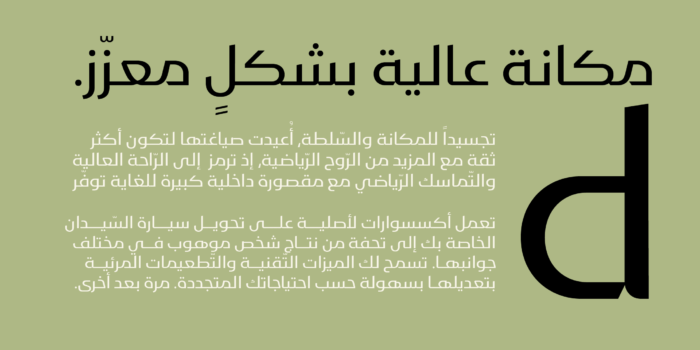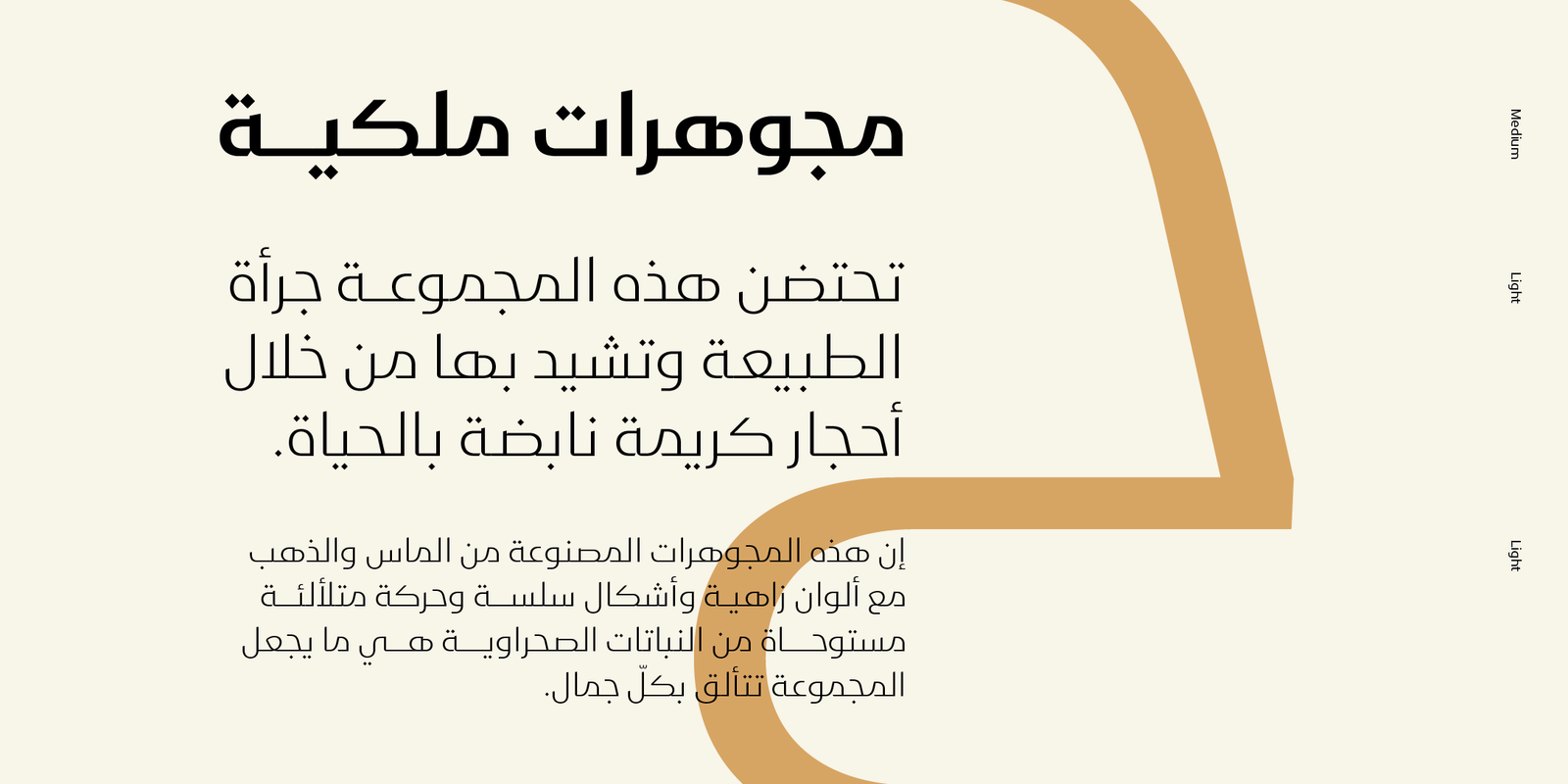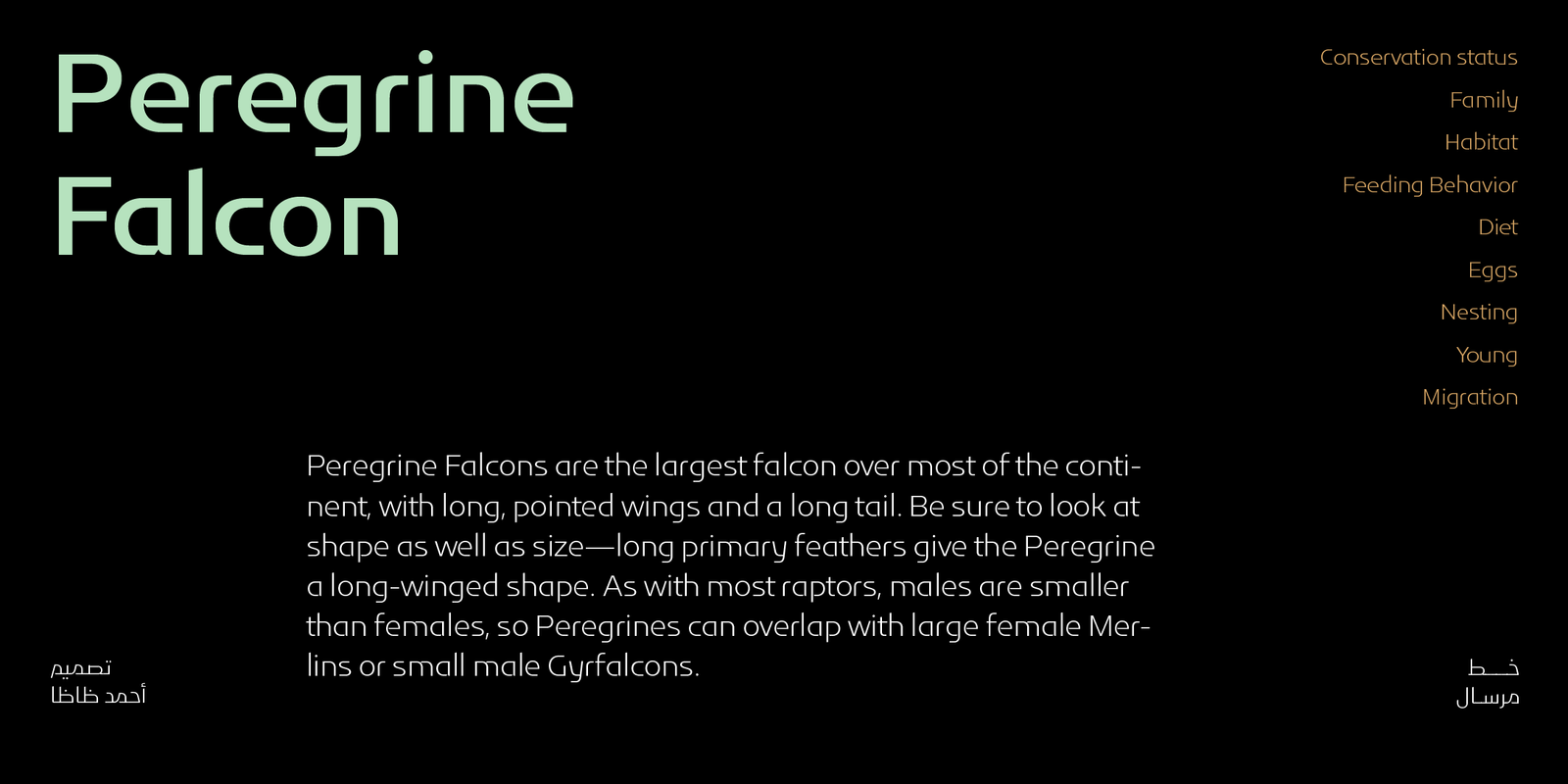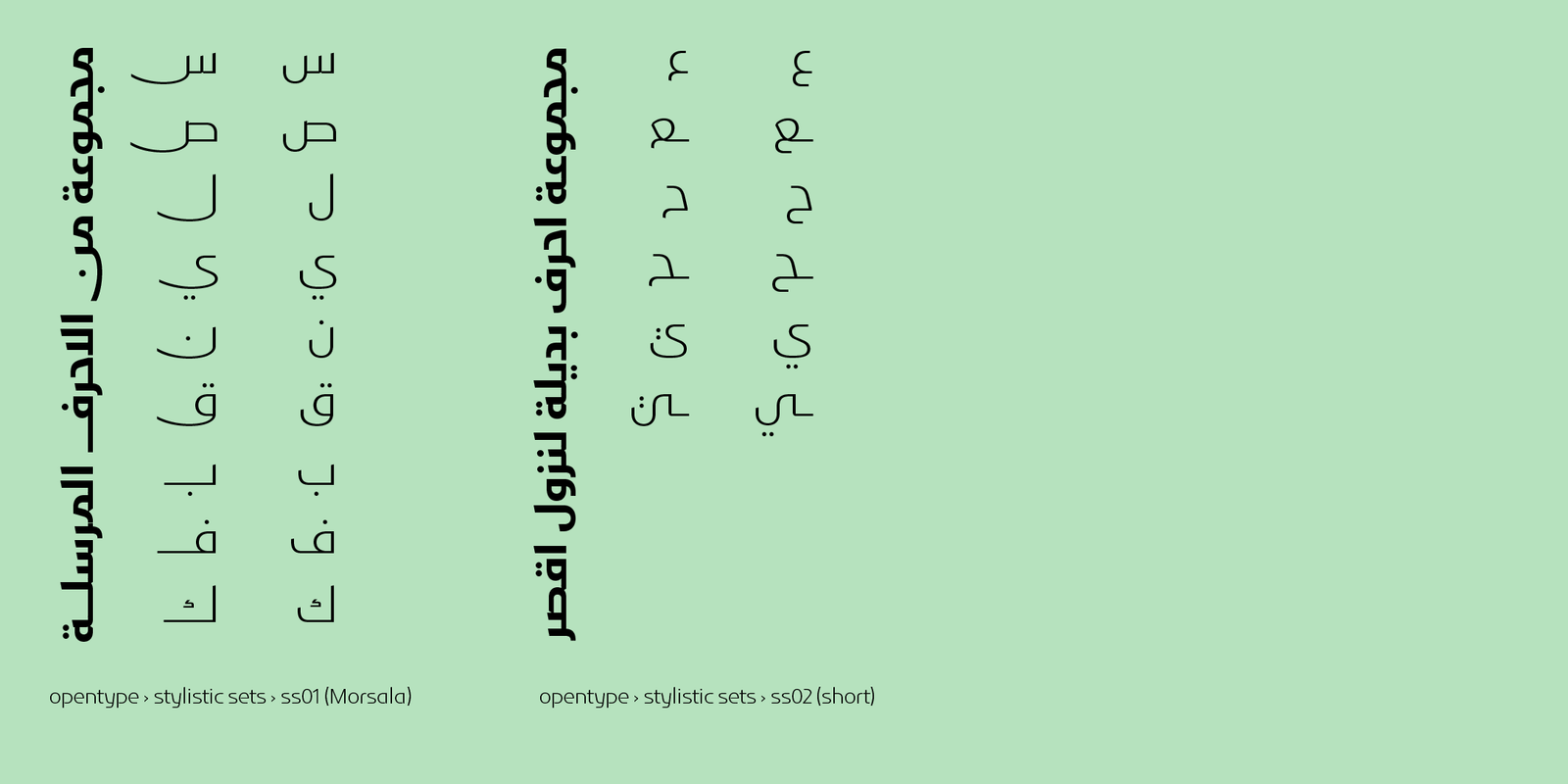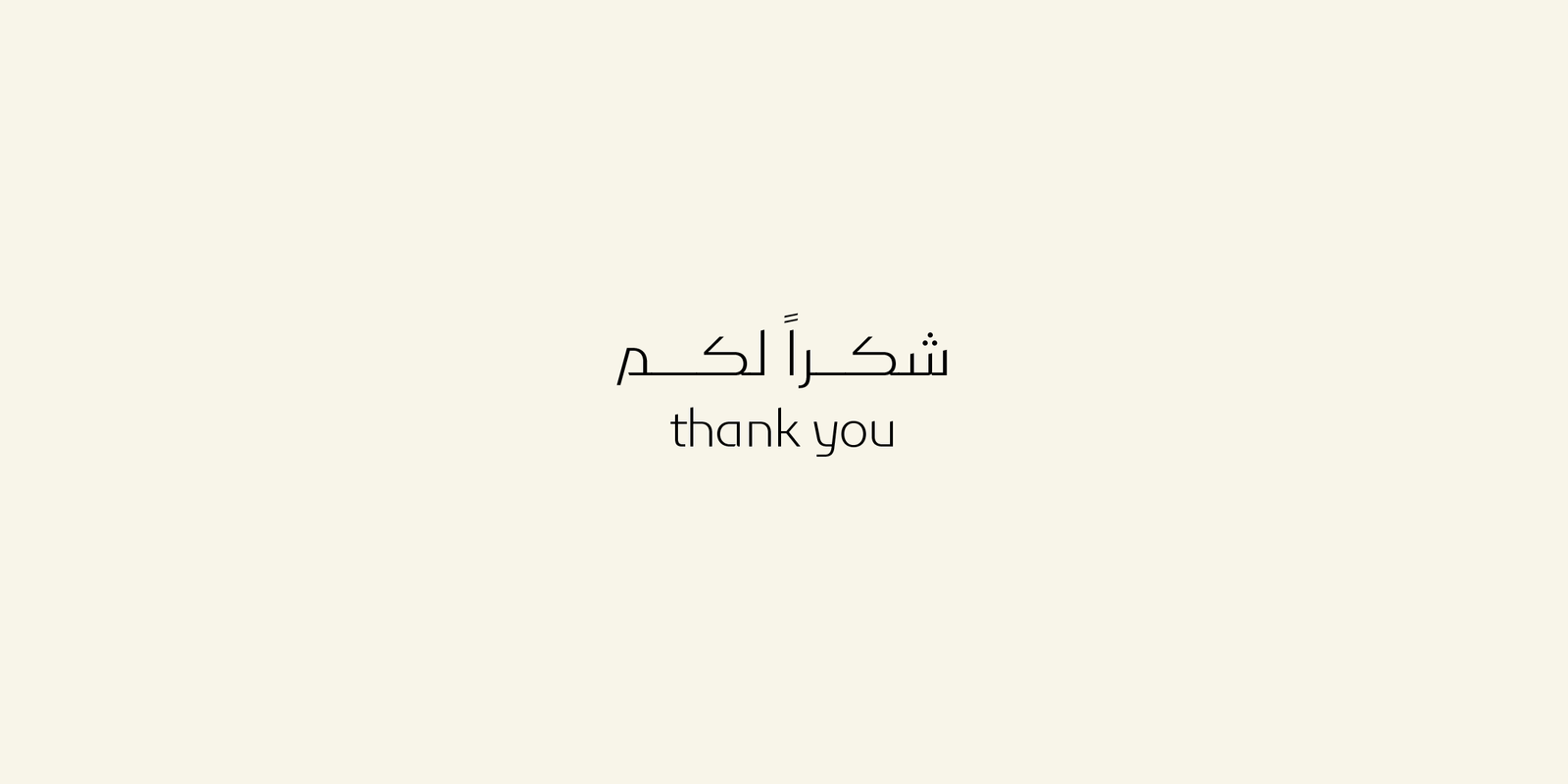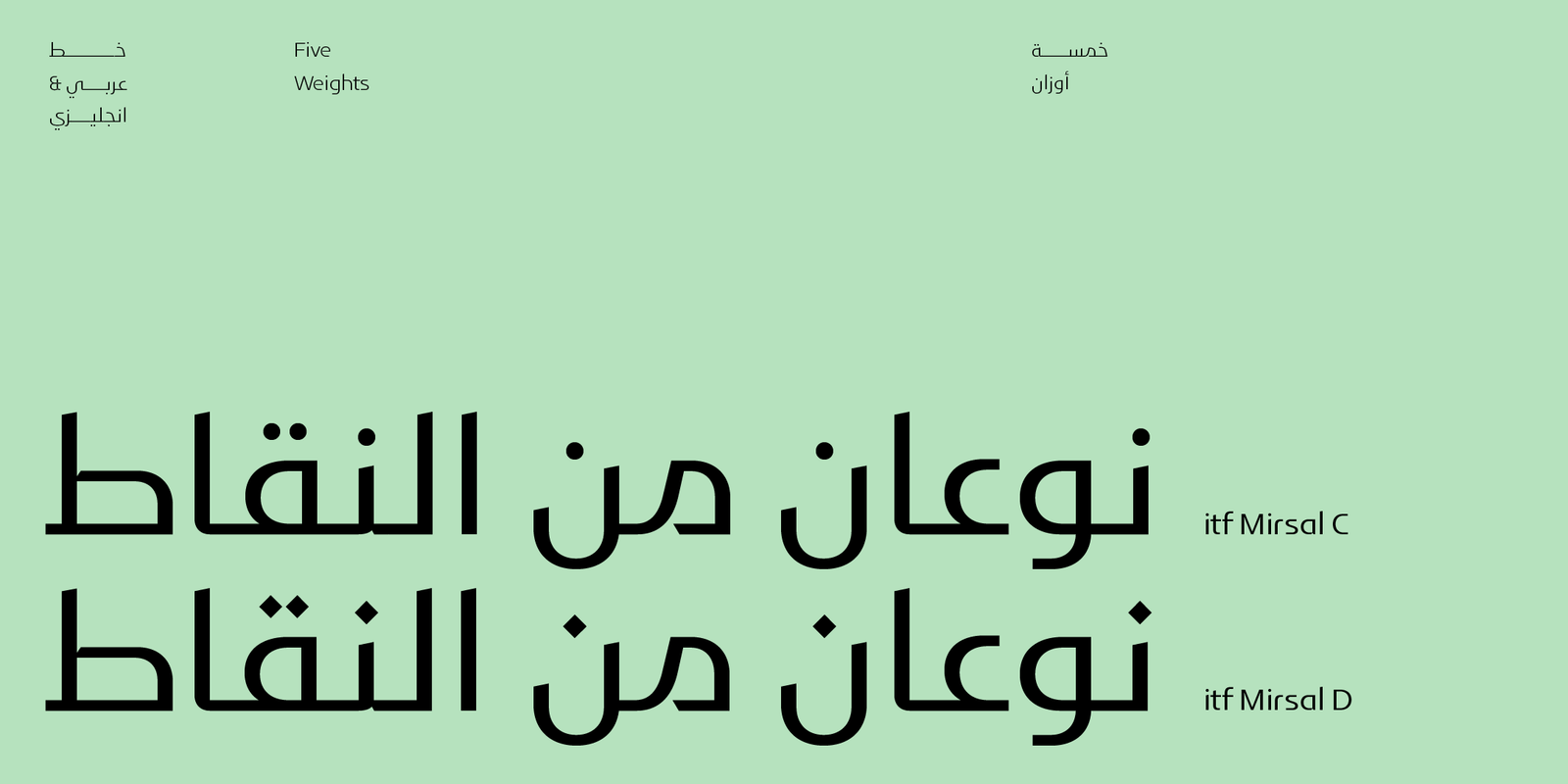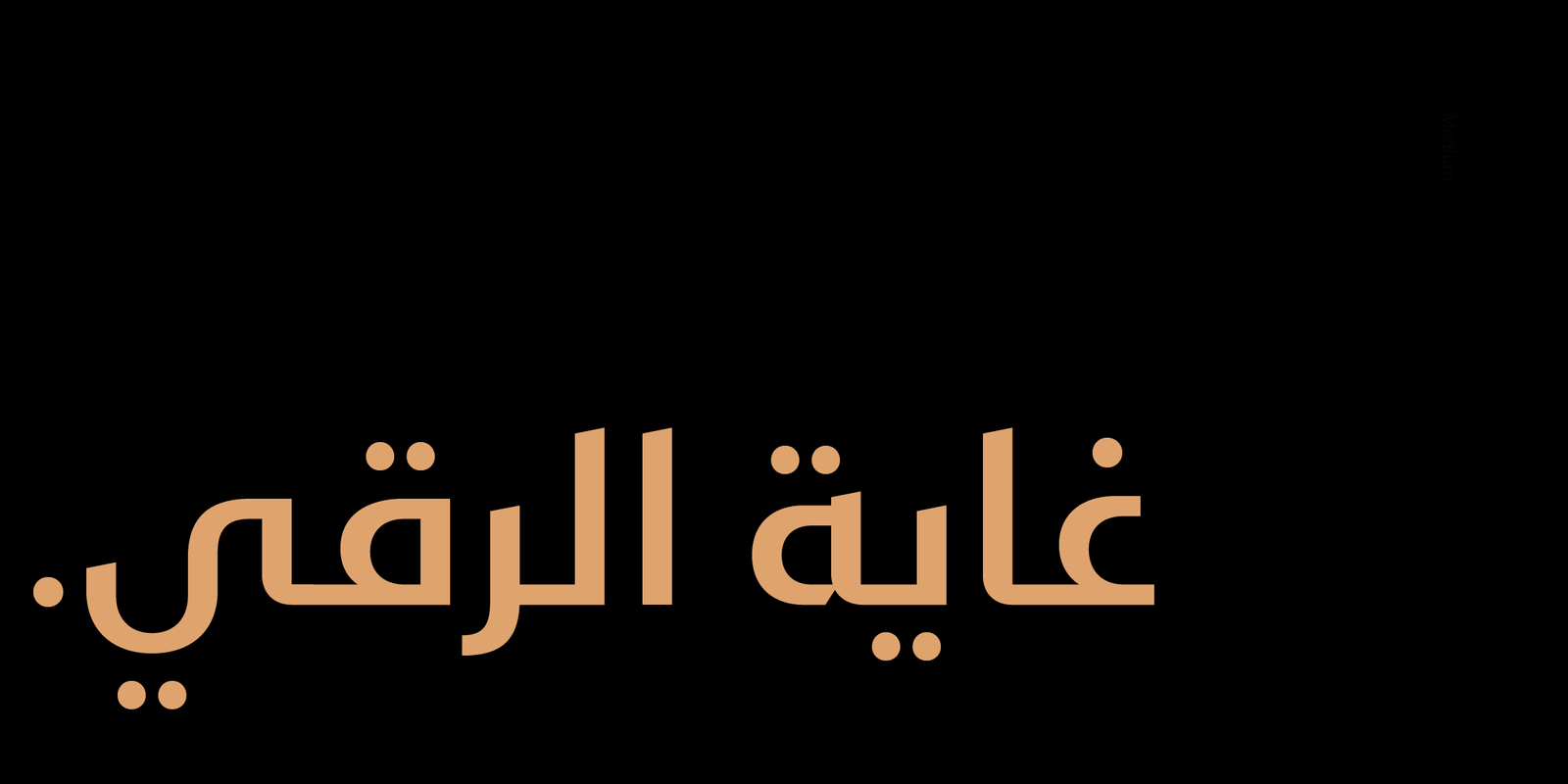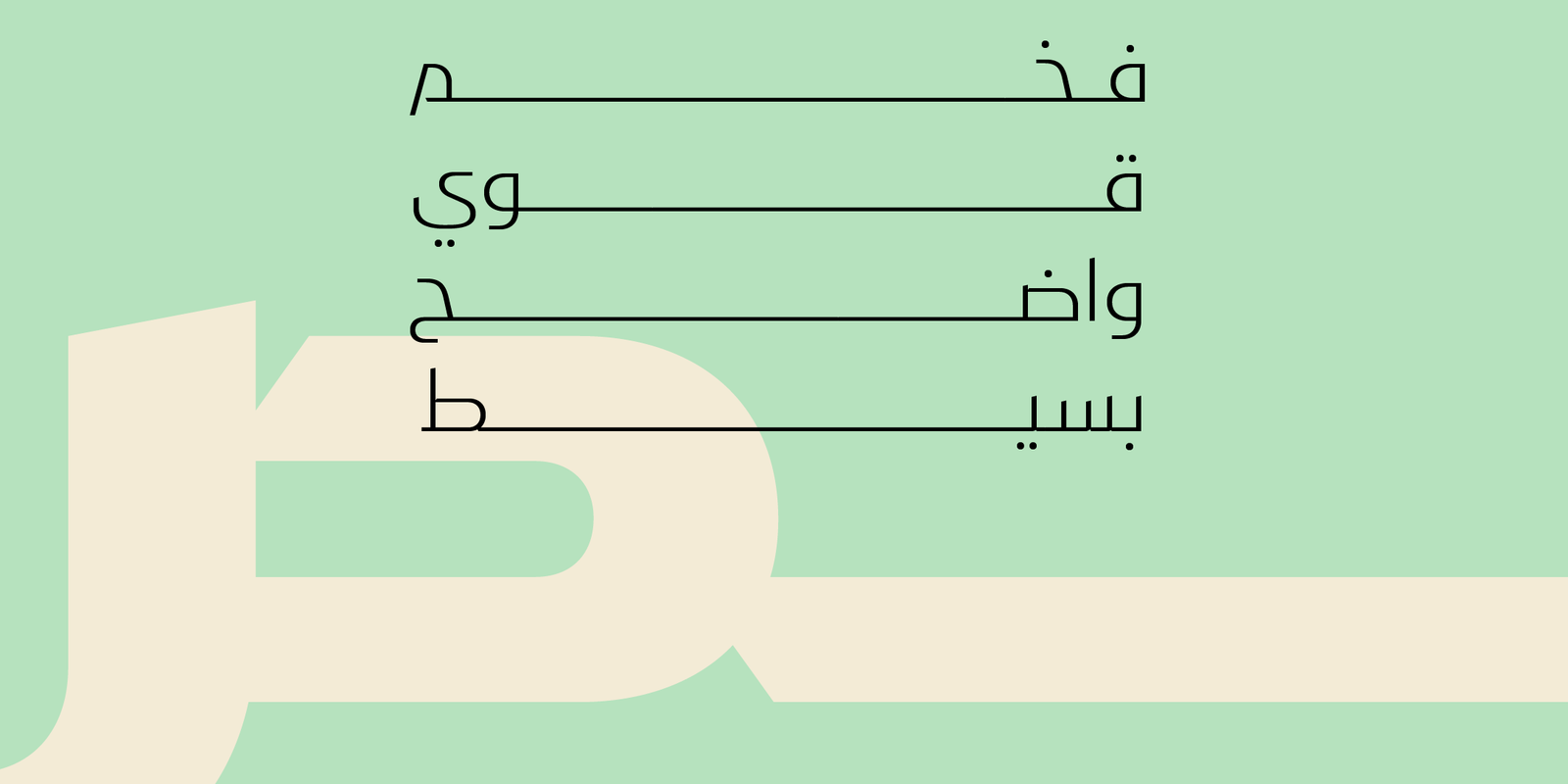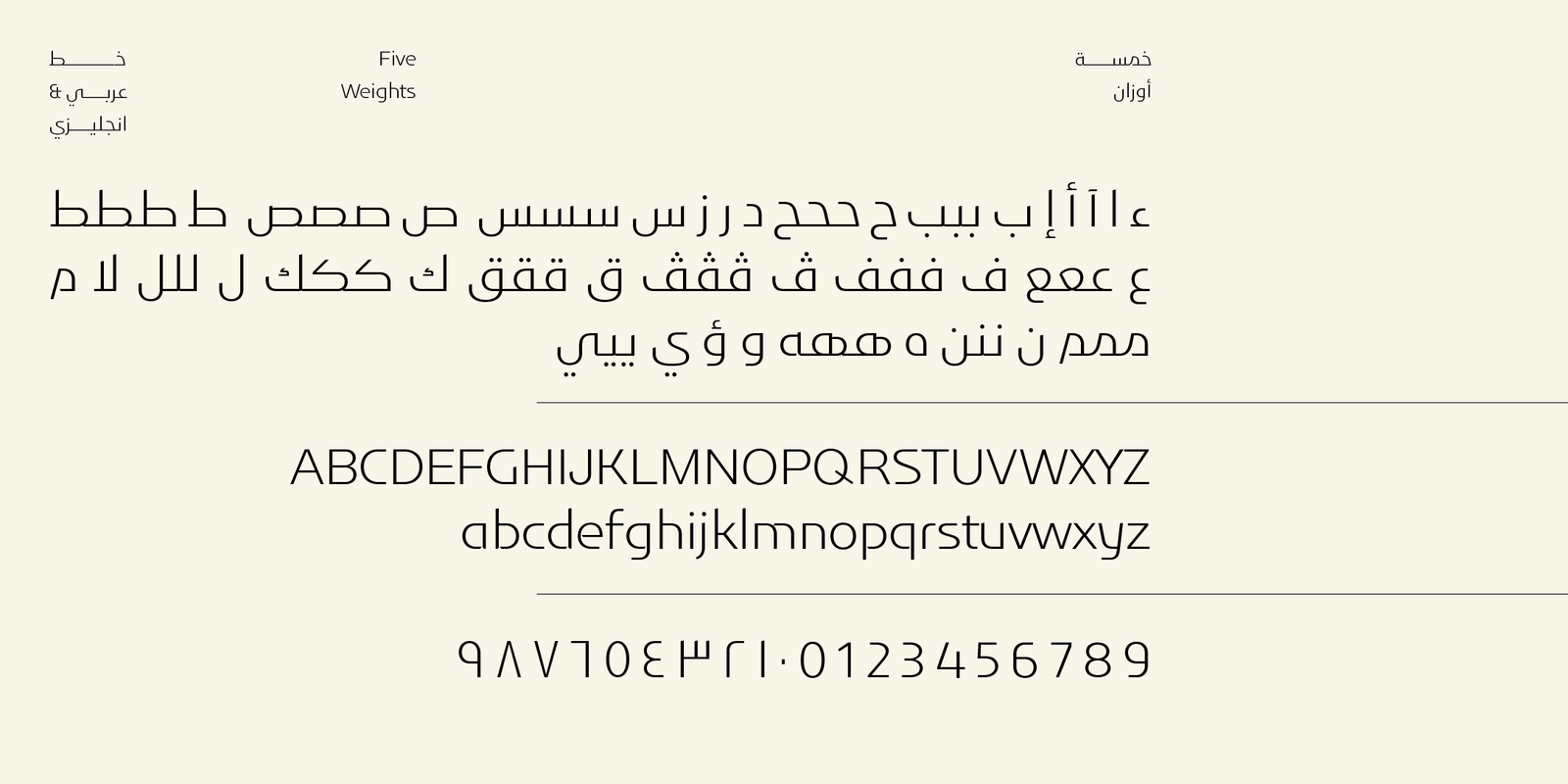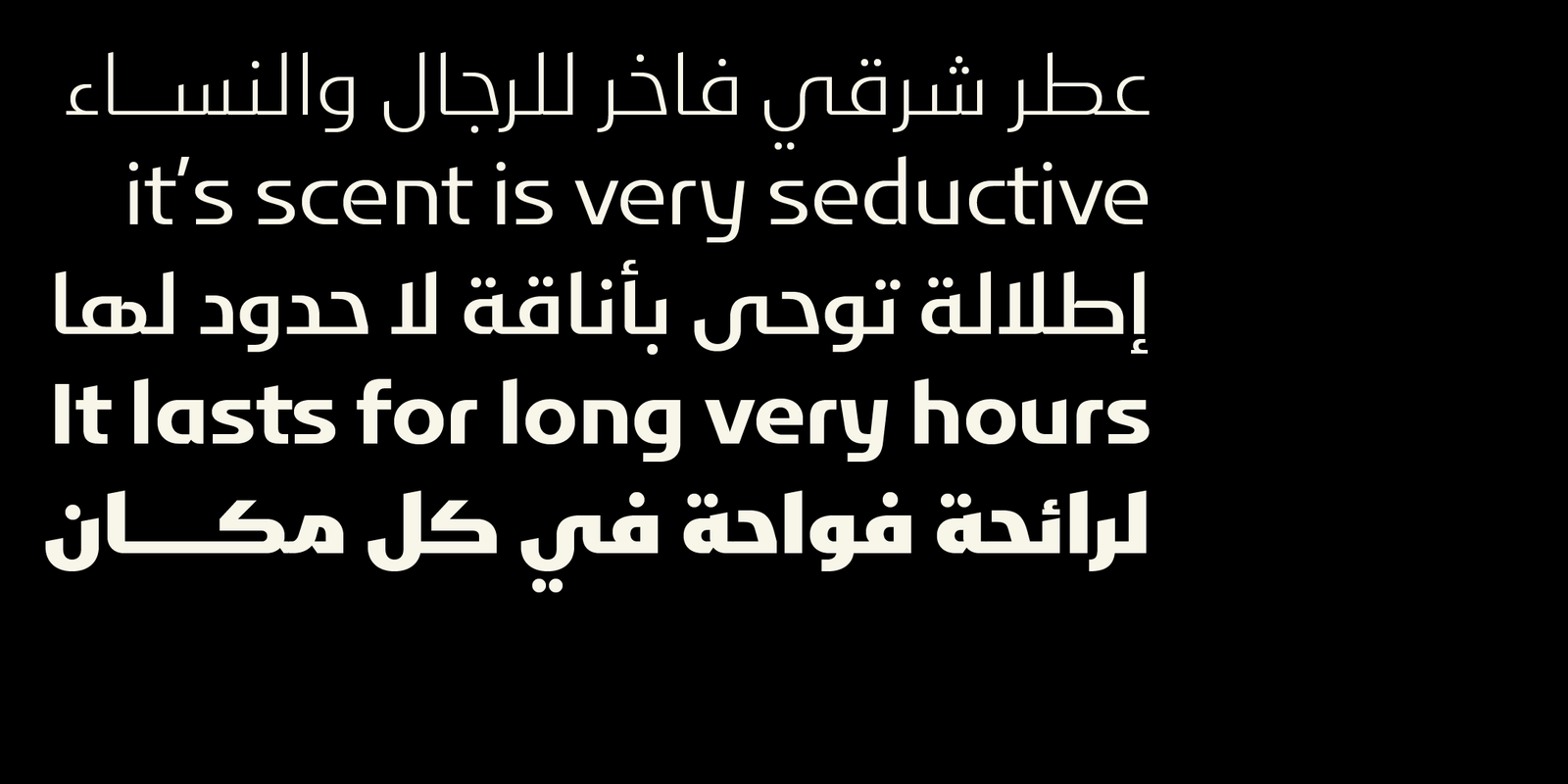
Mirsal Arabic typeface – خط مرسال
Mirsal Arabic typeface is a modern Arabic typeface designed by Ahmed Zaza. the design is inspired by the Kufi calligraphic style and influenced by the Naskh style. The result is a hybrid that combines modern proportions with Classic Arabic scriptsit’s suitable for branding, editorial, packaging, and advertising.Mirsal Arabic Features five weights from Light to Black.
مرسال هو خط عربي حديث. التصميم مستوحى من الخط الكوفي والنسخ. والنتيجة هي مزيج يجمع بين النسب الحديثة والخطوط العربية الكلاسيكية.
مناسب للعلامات التجارية، والتحرير، والتغليف، والإعلانات. يتميز خط مرسال بخمسة أوزان تتراوح من الخفيف إلى الأسود.
اللغات: العربية والانجليزية
الاوزان : خمسة اوزان
المميزات:
• نوعان من النقاط كل نوع في خط منفصل
• أحرف بديلة لنزول اقصر
• أحرف مرسلة